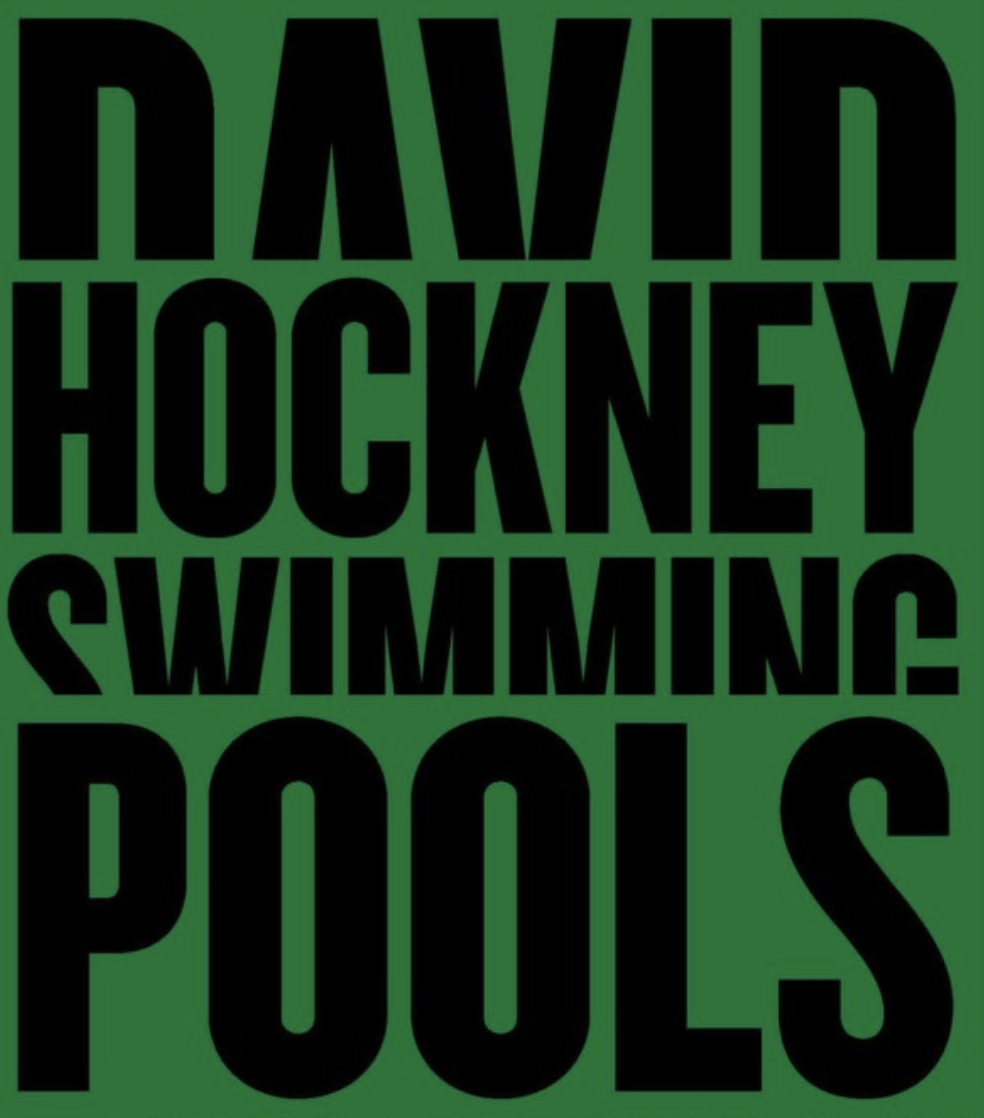
Moderne, schmallaufende Groteske
Ich bin auf der Suche nach einer schmallaufenden Grotesken – ein bisschen Bureau Grotesk-like aber moderner und geradliniger.
Anbei ein Bild wohin die Reise gehen soll. Vielleicht kennt die auch jemand und kann mir ähnliche beim Namen nennen?